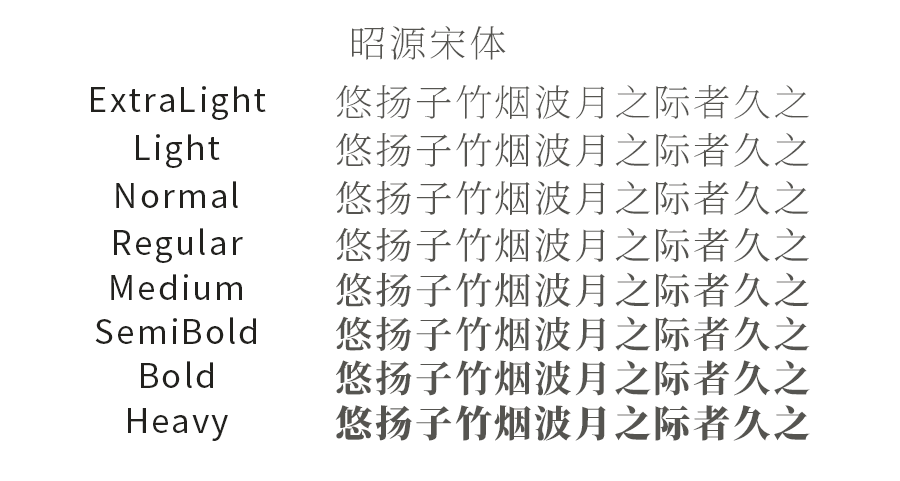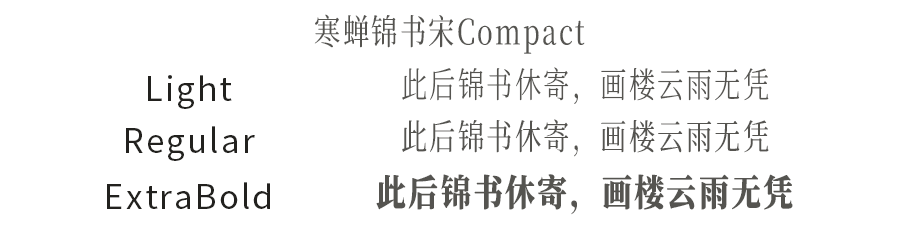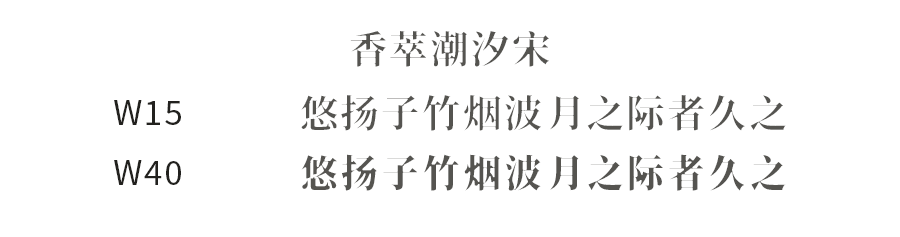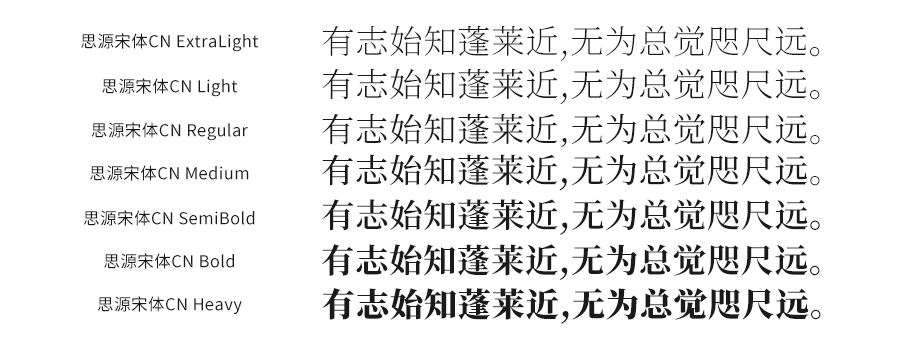
由Adobe出品的思源宋体是“思源黑体”的宋体版兄弟,覆盖简体中文、繁体中文、日语、韩语四种东亚语言,7种字重(从纤细到粗黑)共65,540个字形。无论是做多语言海报、双语PPT,还是设计跨国品牌LOGo,它都能保持一致的视觉美感。
这款字体把宋体的“棱角”变成了“圆弧”,笔画间还偷偷加了粘连设计,像被水墨晕染过一样柔和。横画细如发丝,竖画粗壮有力,对比强烈却不突兀,自带“小清新+古典雅韵”的混搭气质。这款字体一共有2款字重,选择你适合的下载吧~
作为昭源黑体的“官方CP”,昭源宋体继承了开源免费的基因,收字量超大且字重丰富(从Regular到Bold,一共8款字重哦~)。它的笔画简洁利落,中宫宽松不拥挤,屏幕显示清晰不糊,打印出来也依然精致。
基于思源宋体改造的寒蝉锦书宋,把直角变圆角,还重新调整了字重比例,粗细更均衡。它的Compact窄体版本特别适合窄栏排版,比如杂志内页、电子书目录或长文本标题,既节省空间又保证可读性。